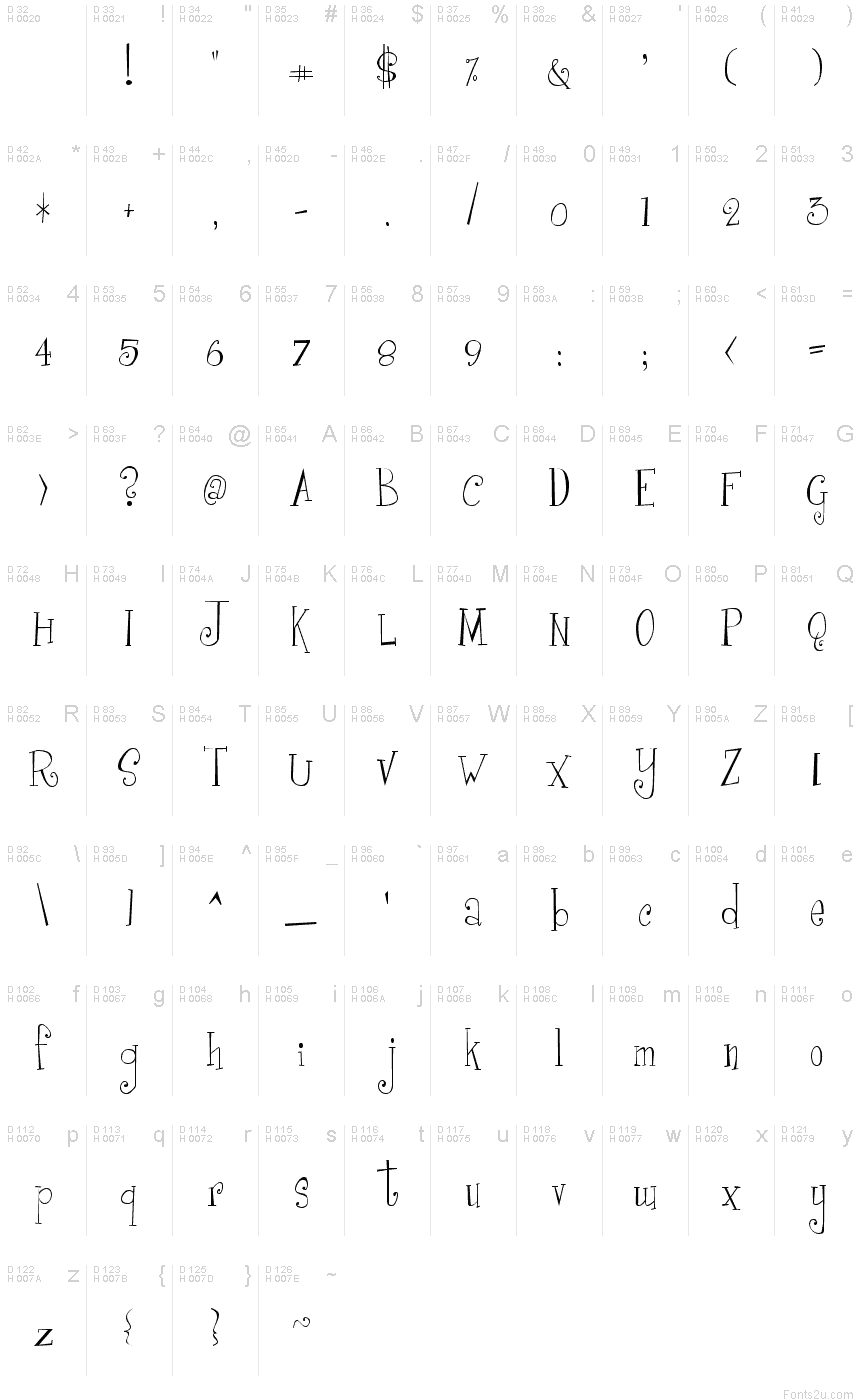
Girls are Weird von John Martz ist eine kostenlose, dekorative Handschrift. Die hohen, drahtigen Buchstaben wirken unruhig und eigenwillig, während die geschwungenen Enden eine Mischung aus gruselig und süß verströmen – wie Kritzeleien am Rand eines alten Notizbuchs. Durch die unregelmäßigen Striche und verspielten Schnörkel wirkt die Schrift rau und fast wie mit Tinte gezeichnet, wodurch sie sich wunderbar von der Masse an glatten, generischen Skript-Fonts abhebt.
Mit Girls are Weird verleihen Sie Ihren Überschriften sofort einen ausgefallenen Charakter – perfekt für Zines, Einladungen, Jugendbuchcover, Bastelverpackungen, Poster oder Social-Media-Grafiken. Am besten kommt diese kostenlose Schrift groß und fett zur Geltung, damit die Schlaufen und Wendungen richtig wirken können. Kombinieren Sie sie für den Fließtext mit einer schlichten, minimalistischen serifenlosen Schrift, damit das „Verrückte“ voll zur Geltung kommt, ohne das Layout zu überladen.